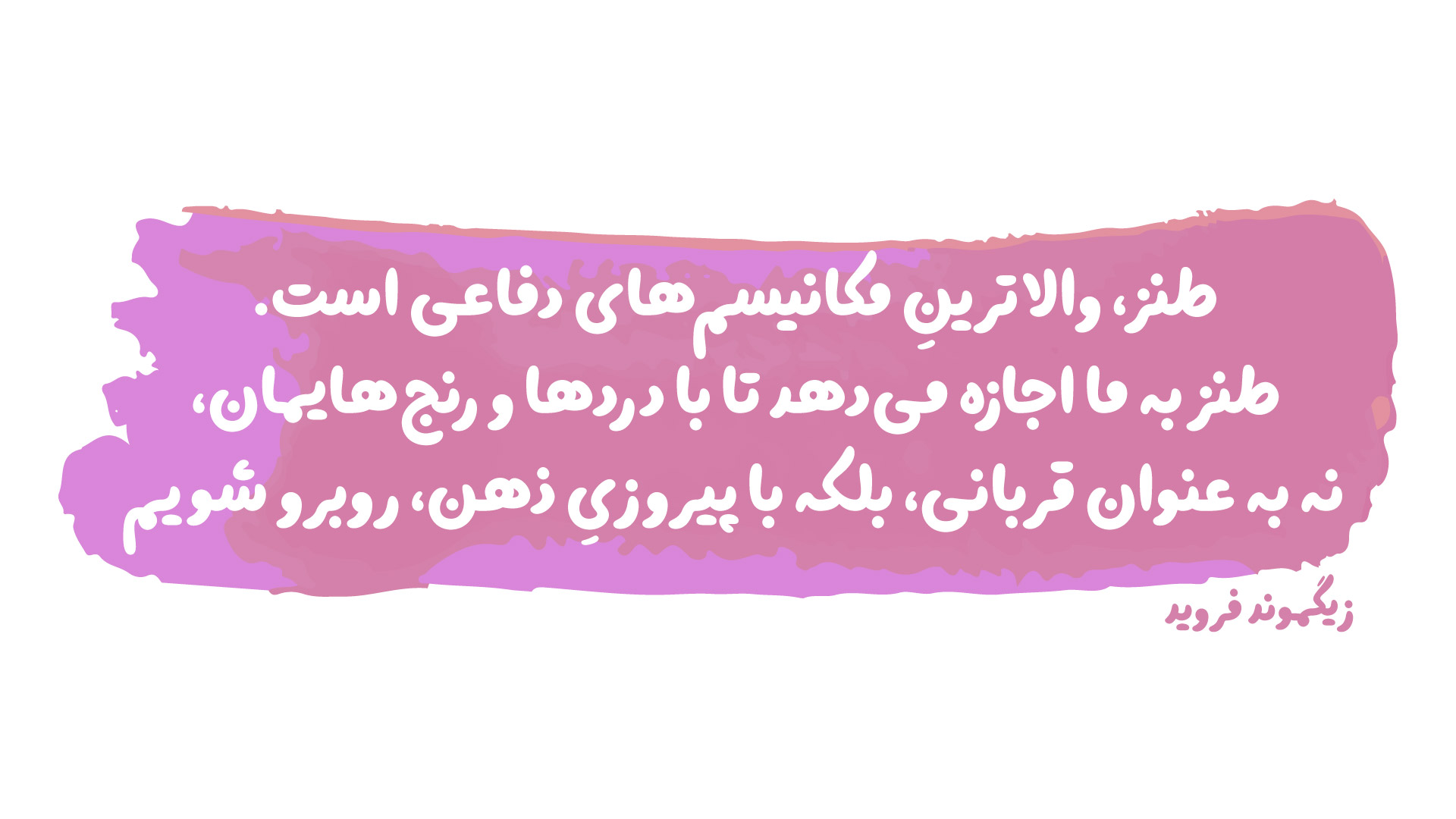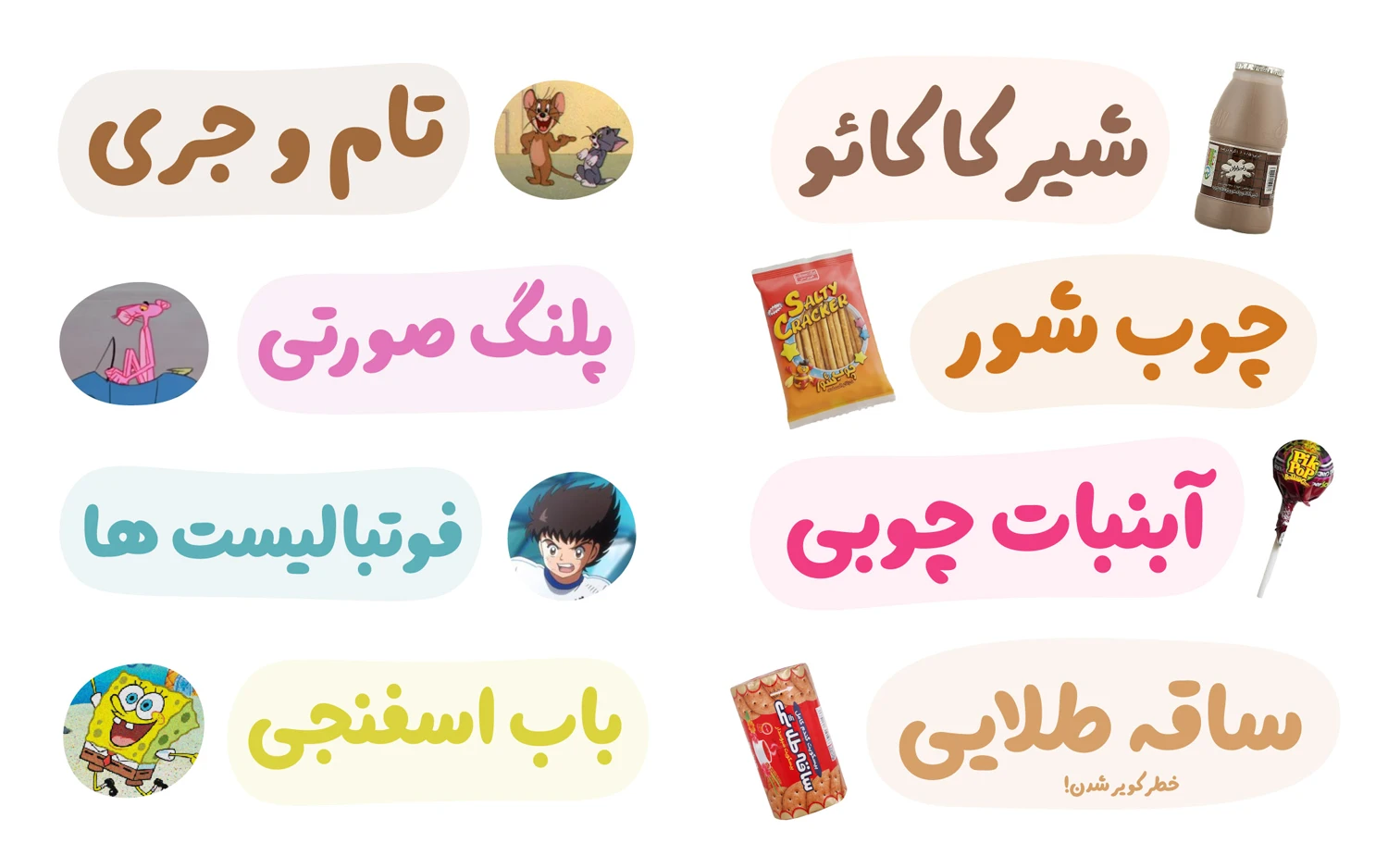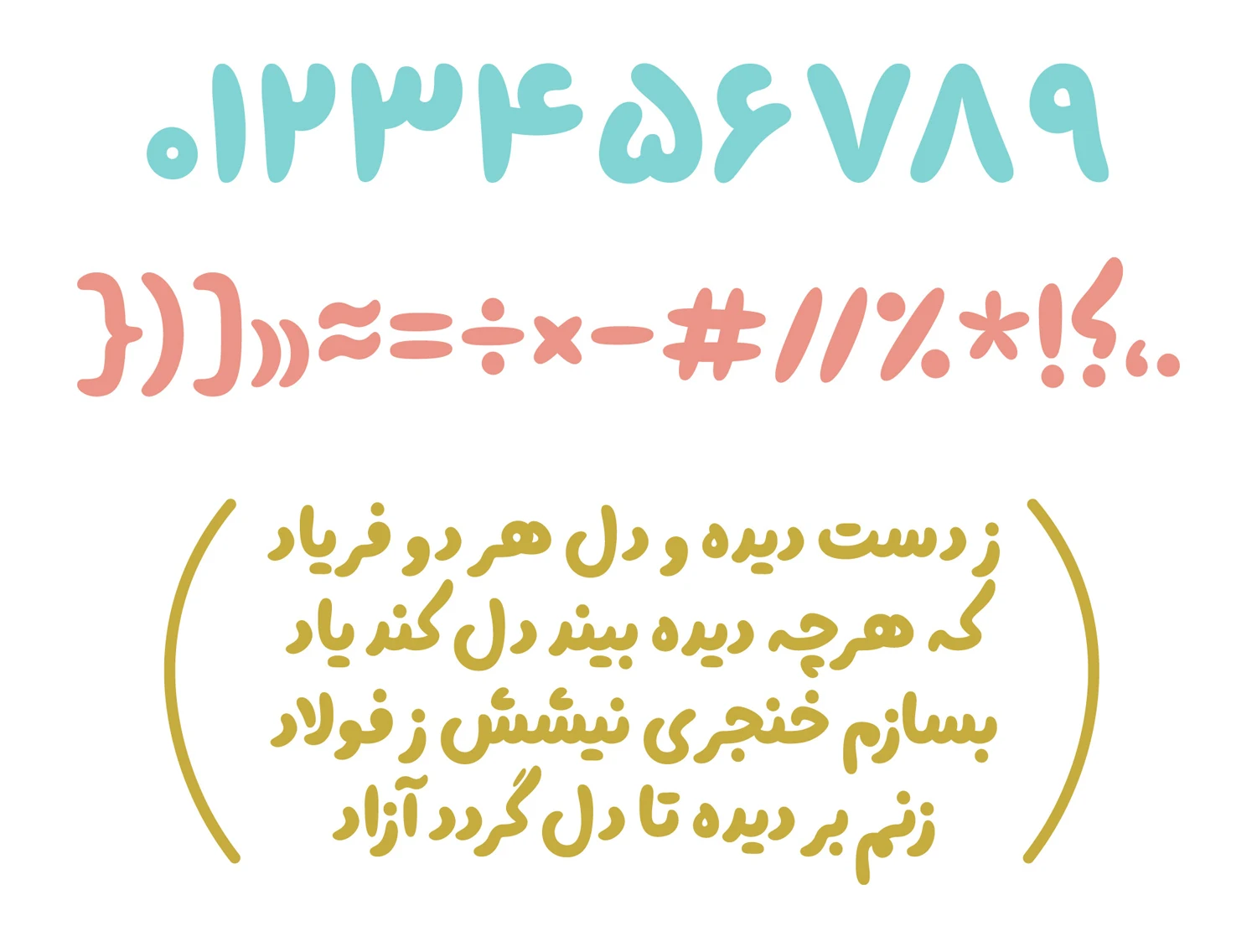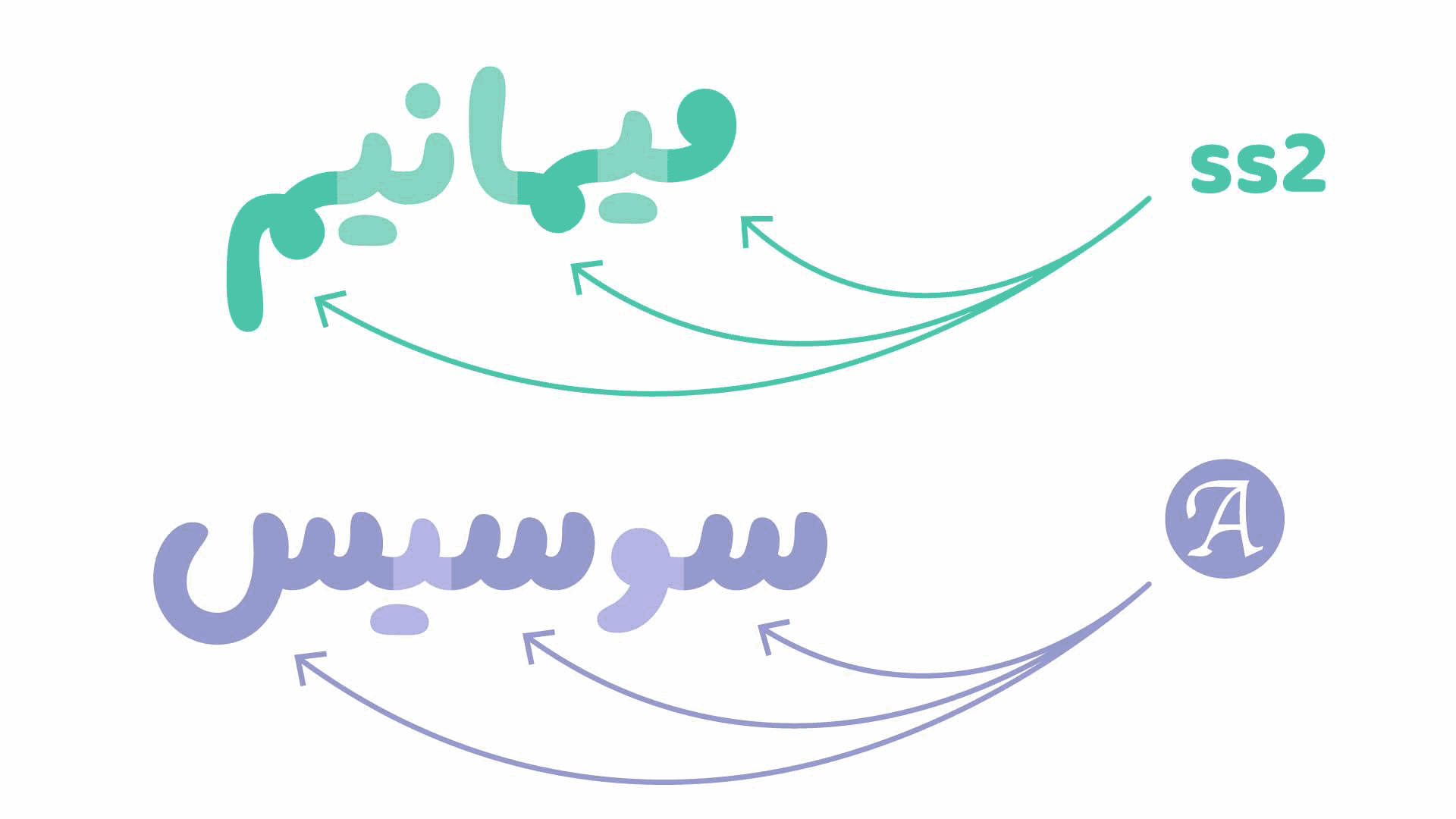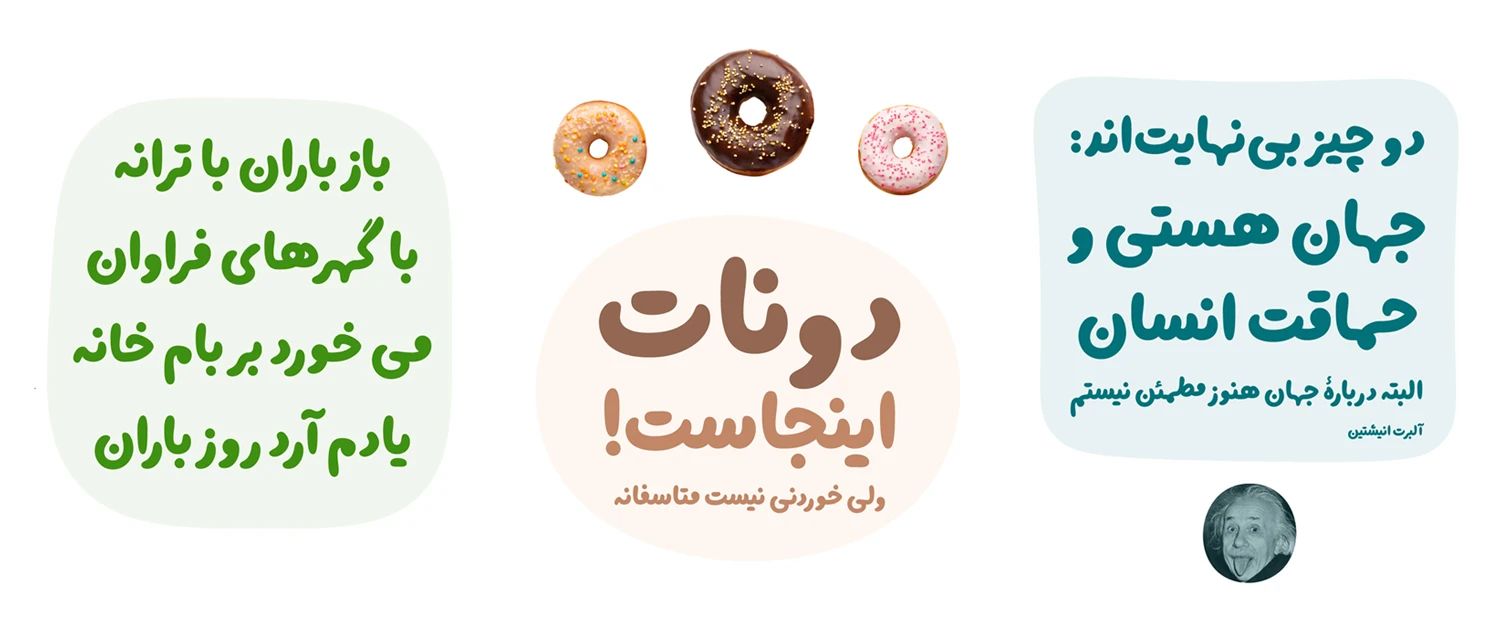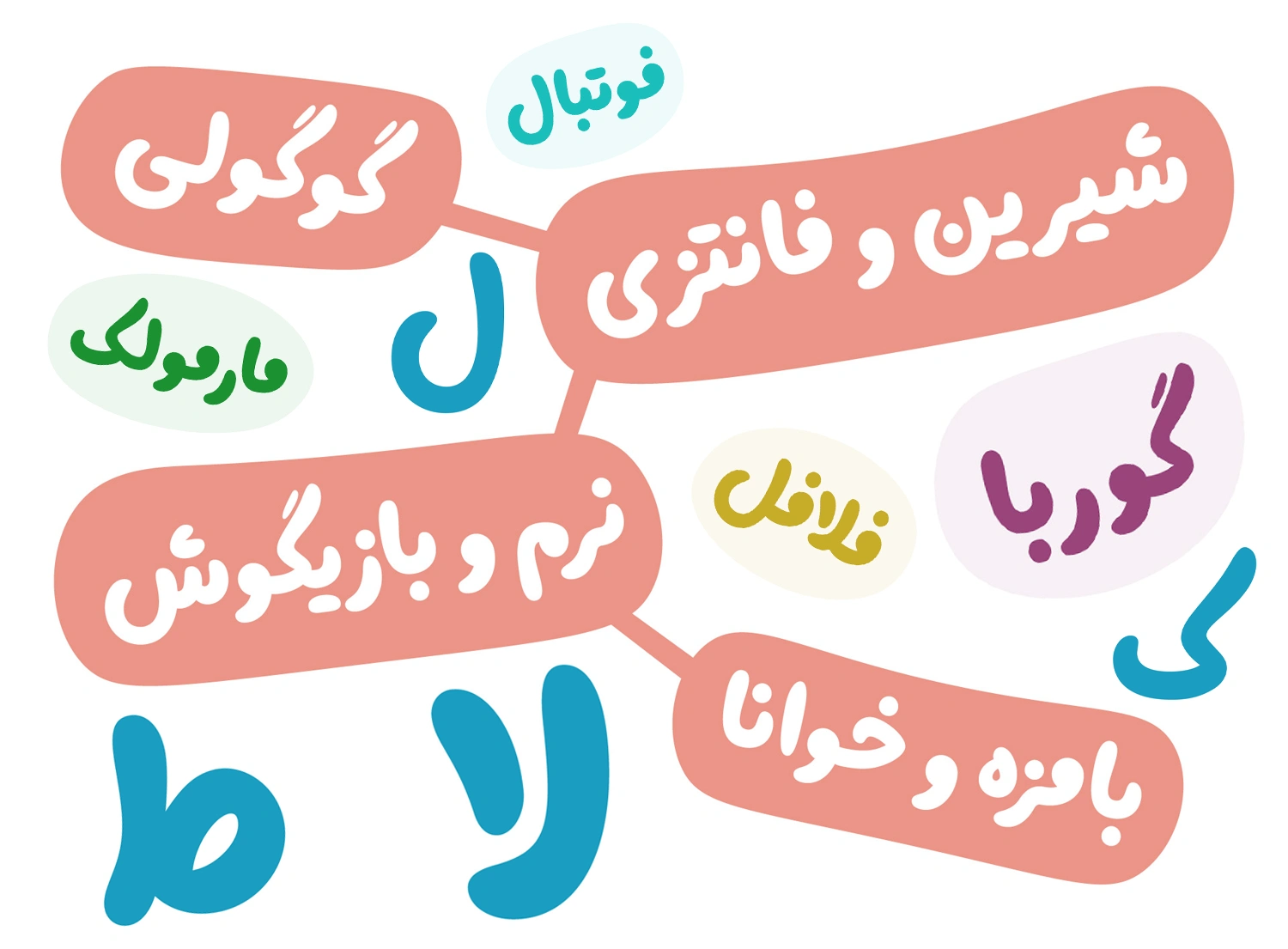
فونت دونات (donut)
فونت دونات (به انگلیسی: donut) از سری فونتهای فانتزی است که بر اساس دستخط شخصی طراحی شده است. در این فونت که ساختاری کاملا دوستانه دارد، با یک وزن نسبتا سیاه و Black سروکار داریم. شکلگیری این قلم از طراحی عکس نوشتهها شروع شد که با استقبال کاربران از این سبک نوشتاری، باعث ایجاد ایده تبدیل آن به فونت شد.
علی پیروی دستخط خود را برای ساخت این فونت بارها مورد بازبینی قرار داد تا با بازطراحی و تغییر شکل حروف، یک فونت فارسی استاندارد و زیبا از درون آن متولد شود. همین وسواس به فونت هویت منحصربهفردی داد که خروجی آن نسخه پیشرو است.
نقد و بررسی فونت دونات (donut)
قلم دونات دارای یک وزن Black است که میتوانید از آن در متون کوتاه که عموما میتوانید شامل عناوین پستهای شبکههای اجتماعی، طراحی تامنیل، بستهبندی محصولات، عناوین کتاب کودک و نوجوان یا طراحی پوسترهای خلاقانهای باشد که عموما جریان صمیمیت را برای انتقال محتوا نشانه میگیرند.
این فونت دستنویس که در نقطهگذاری آن نیز از نقاط پیوسته استفاده شده، حال خوب و انرژی مثبت را به مخاطب منتقل میکند. به منظور نمایشیتر کردن فونت، امکان استفاده از حروف و ترکیبات جایگزین نیز فراهم شده است. میتوانید ترکیباتی مانند «ـیـ، ـم» را از طریق ابزار Stylish Set نرمافزارهای گرافیکی مثل فتوشاپ در چند حالت مختلف تایپ کنید. یا با استفاده از ابزارهای دیگر امکان ایجاد کشیدگی در حروفی مانند «س، ش» را که ساختاری بدون دندانه دارند را پیادهسازی کنید.
این فونت فارسی از زبان عربی پشتیبانی کاملی دارد و گلیف اعداد نیز به شکل استاندارد روی آن پیادهسازی شده است. جهت بررسی دقیقتر فونت میتوانید از نمونه تصاویر زیر آن را بیشتر مورد ارزیابی قرار دهید.